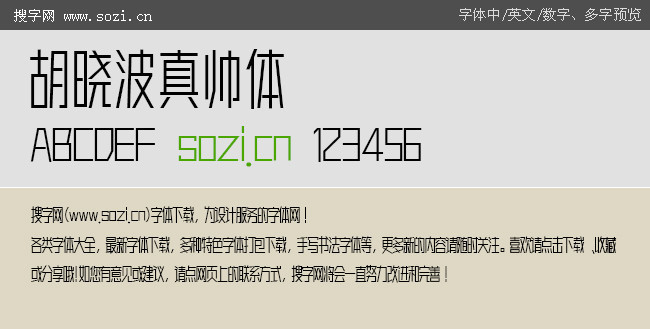
胡曉波真帥體
搜字網(wǎng)給大家提供一款胡曉波真帥體字體中文字體下載,胡曉波真帥體是由設(shè)計(jì)者胡曉波推出的三款免費(fèi)商用字體之一,字體采用了細(xì)長(zhǎng)形字體設(shè)計(jì)。適用于大標(biāo)題、包裝設(shè)計(jì)、海報(bào)設(shè)計(jì)等應(yīng)用。